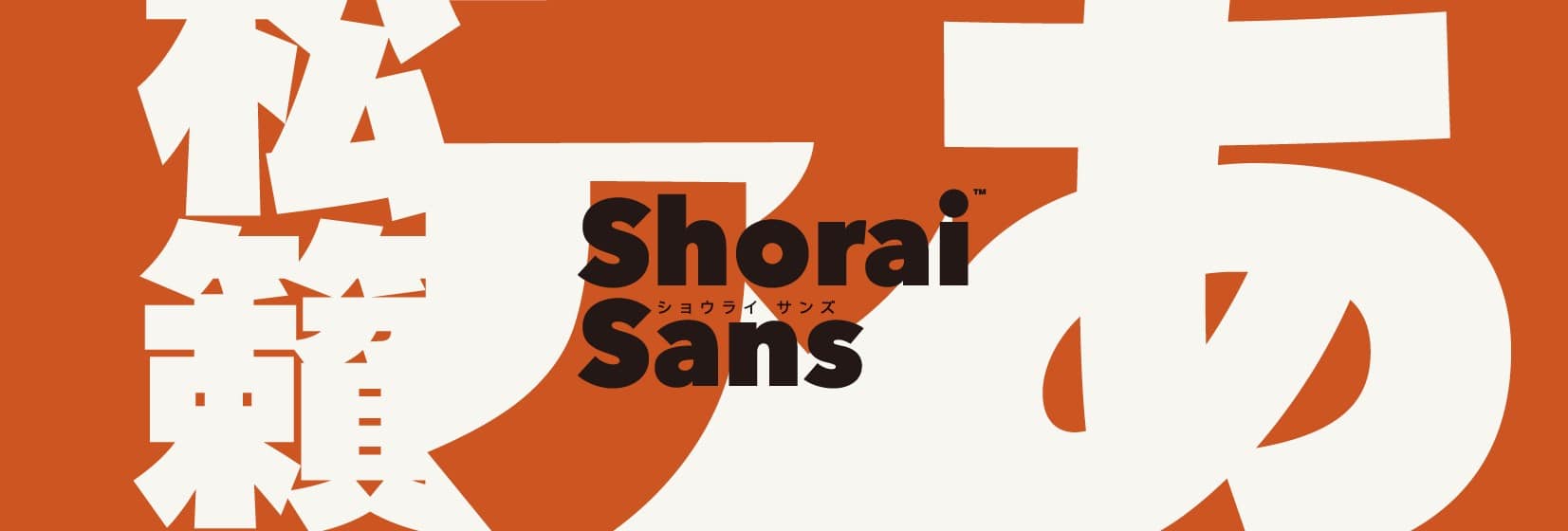
Shorai™ Sans ist eine geometrische serifenlose Schrift, die subtile Nuancen und ein nahezu unbegrenztes Spektrum von Anwendungen bietet. Die von Yukihiro Nakamura, Akira Kobayashi, Ryota Doi und dem Monotype Studio entworfene Shorai Sans eröffnet neue Horizonte in der japanischen Typografie.
Shorai Sans ist nach Tazugane Gothic die zweite japanische Schrift aus dem Hause Monotype, die mit dem Gedanken entwickelt wurde, die Bandbreite und Züge der Avenir Next zu kombinieren. Das Ergebnis überzeugt mit Eleganz, Charakter sowie viel Ausdruck und erfüllt die Bedürfnisse und Erwartungen von Designern in einer modernen Welt.
Mit ihrer klaren Lesbarkeit und einer Vielfalt an Strichstärken bietet die Shorai-Familie der Kreativwelt eine gesamtheitliche Markenlösung für die internationale Kommunikation. Sie ist eine einfach zu verwendende Schrift, die das Gleichgewicht zwischen japanischem und europäischem Text und den Zeichenabständen optimiert. Das saubere Schriftbild erinnert an die Eleganz von Avenir Next und erhält dabei die Wärme und Originalität der japanischen Handschrift. Die geradlinigen, serifenlosen Schnitte mit feinen Details sind für fast unendlich viele Einsatzbereiche geeignet – vom Publishing über Werbung bis hin zu Websites und technischen Anwendungen. So bietet Shorai Sans die perfekte Lösung für den Austausch zwischen europäischen und japanischen Märkten.
“Wir haben besonderen Fokus daraufgelegt, die Bandbreite der Strichstärken mit einer ‚Heavy Weight‘ zu erweitern, was die Schrift noch eindrucksvoller wirken lässt als die durchschnittliche japanische serifenlose Schrift. Das Resultat ist ein neues Schriftbild, das durch seine moderne Schlichtheit eine neue Generation anspricht“, sagt Creative Type Director Akira Kobayashi.
Type Designer Ryota Doi ergänzt: „Die Ideen von Yukihiro Nakamura sind immer wieder überraschend und spannend. Shorai Sans ist eine Schrift, deren Entwicklung über Generationen stattgefunden hat. Sie ist geradlinig aber spiegelt auf elegante Weise trotzdem handschriftliche Züge – Shorai präsentiert sich mit ihrer robusten Schlichtheit und einer menschlichen Note als japanische Schrift für die Zukunft.“
Nach der erfolgreichen Einführung von Tazugane Gothic im Januar 2017 ist der Bedarf an serifenlosen Schriften im japanischen Markt ständig gestiegen – speziell die Automobilindustrie verlangt nach Schriftbildern, die Solidität und Vertrauen ausstrahlen. Hier findet Shorai künftig ihren Platz und bietet gleichzeitig viele Optionen für Technologie- und Telekommunikationsmarken.